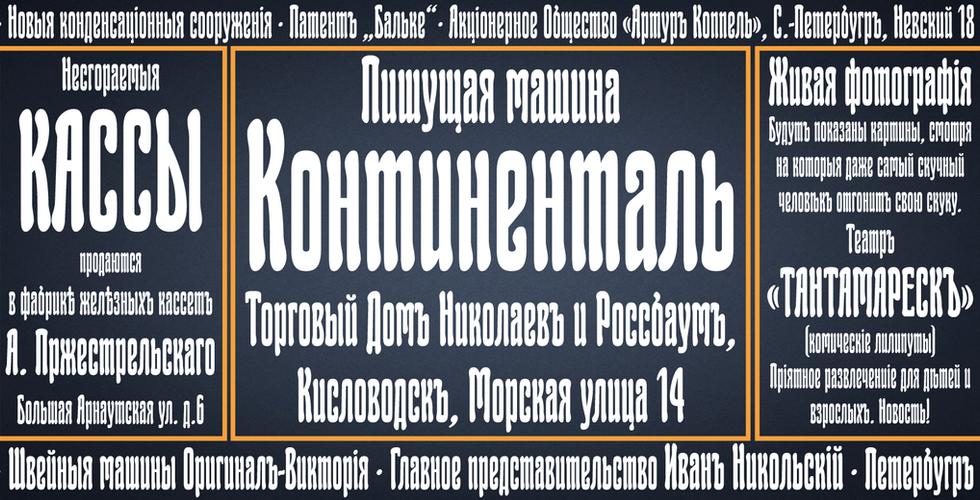
Обновление шрифта Комета/DXKometa
Вышло обновление шрифта Комета. В новой версии переработан рисунок некоторых знаков, добавлены лигатуры, расширена кодировка.
Рекламный шрифт "Комета" (Komet) выпущен в 1907 году Словолитней Б.Кребса (Benjamin Krebs Nachf., Frankfurt a. M., 1907). Цифровая версия шрифта создана в 2015 году на основе оттисков из каталога "Словолитня и фабрика медных линеек Б.Кребс Преемник" Санкт-Петербург и Франкфурт-на-Майне.